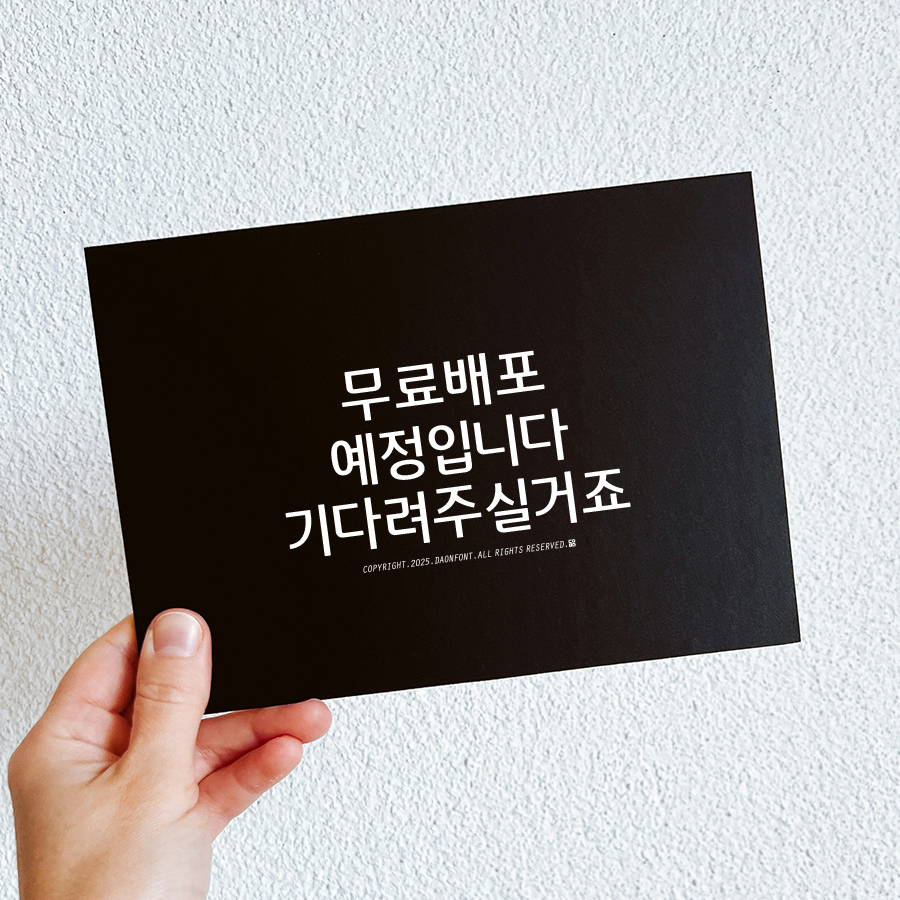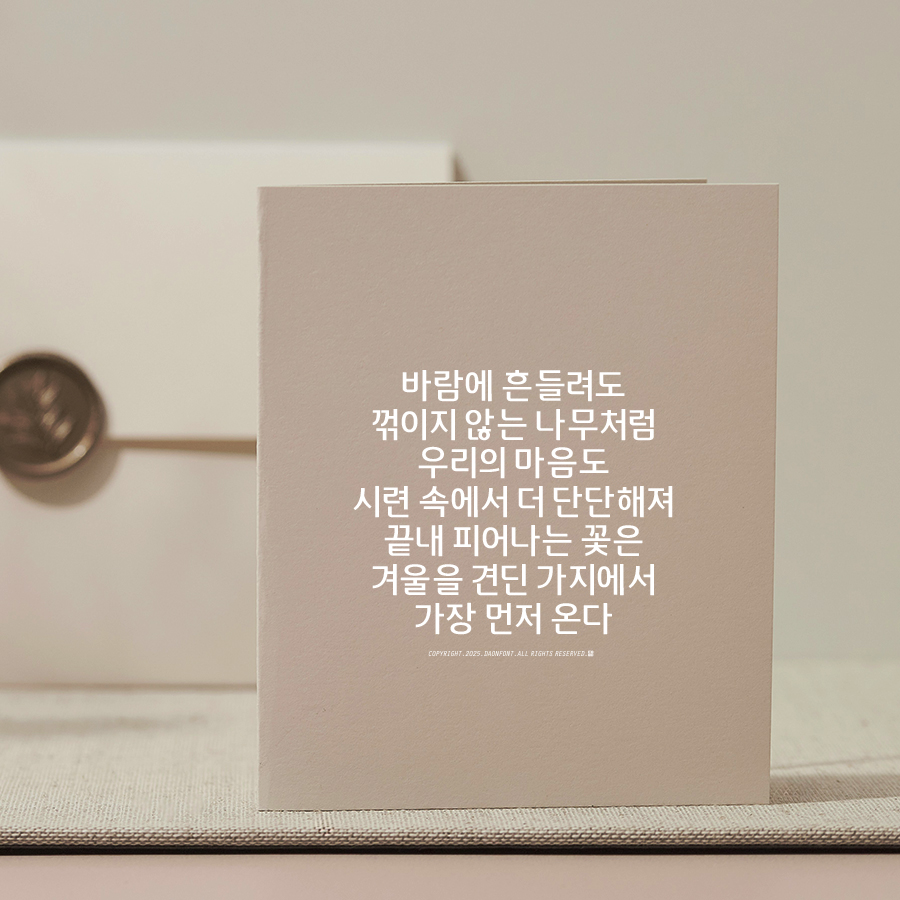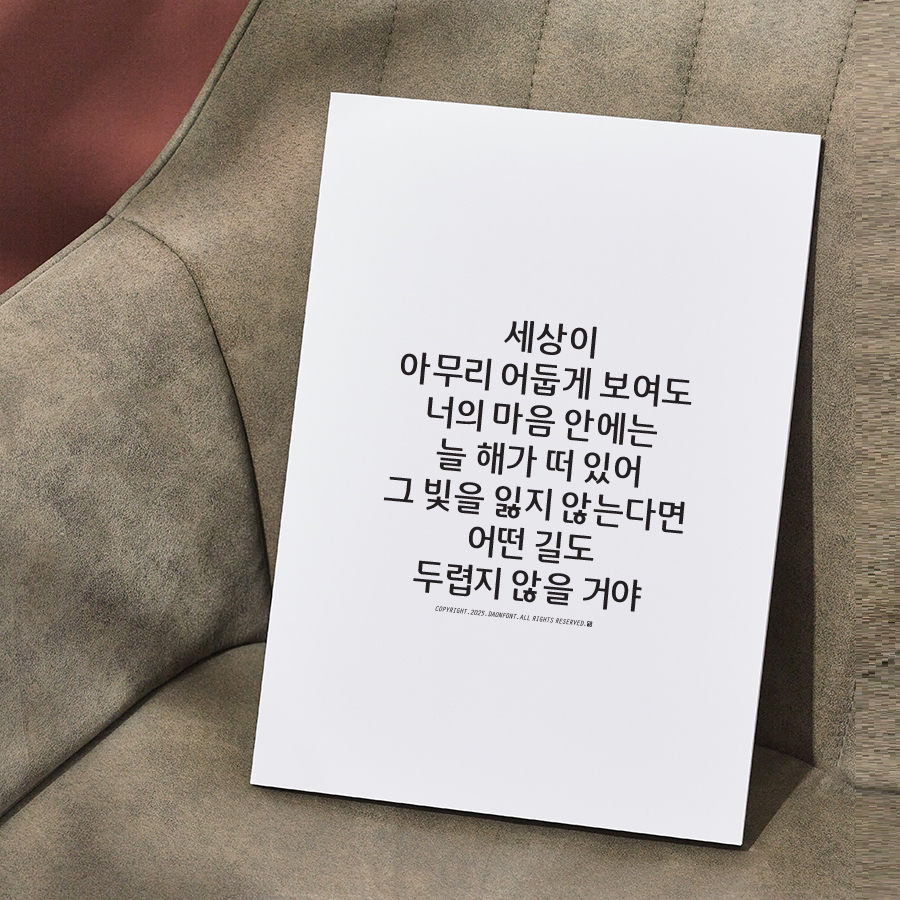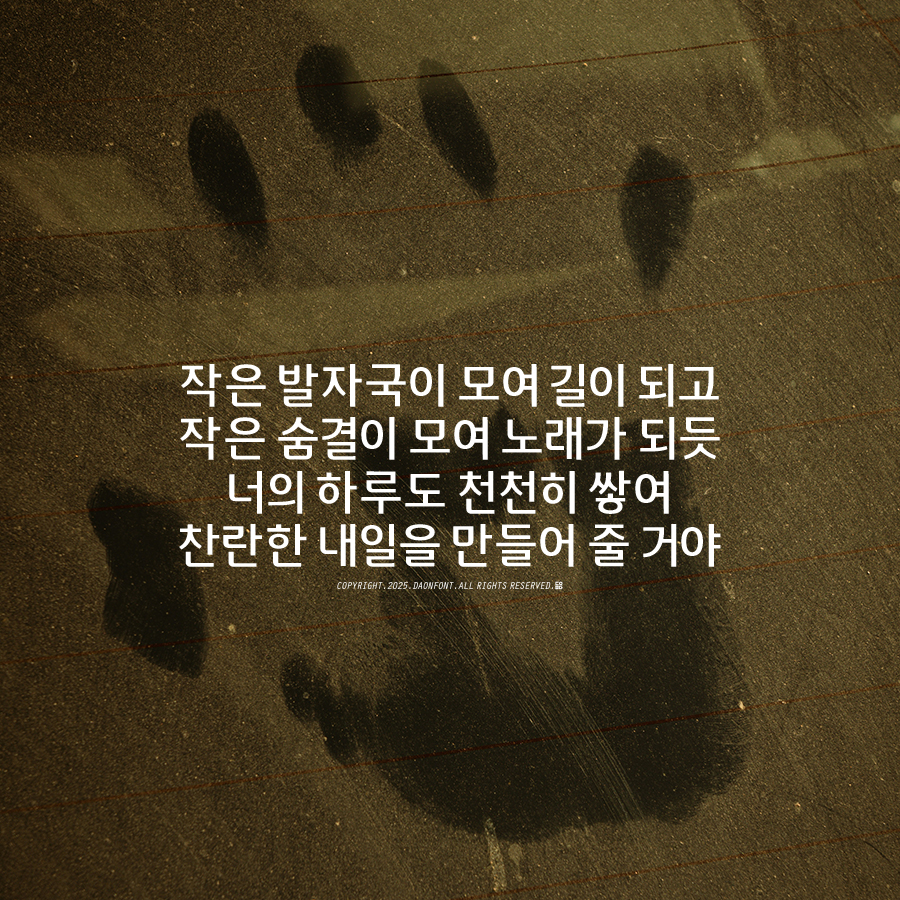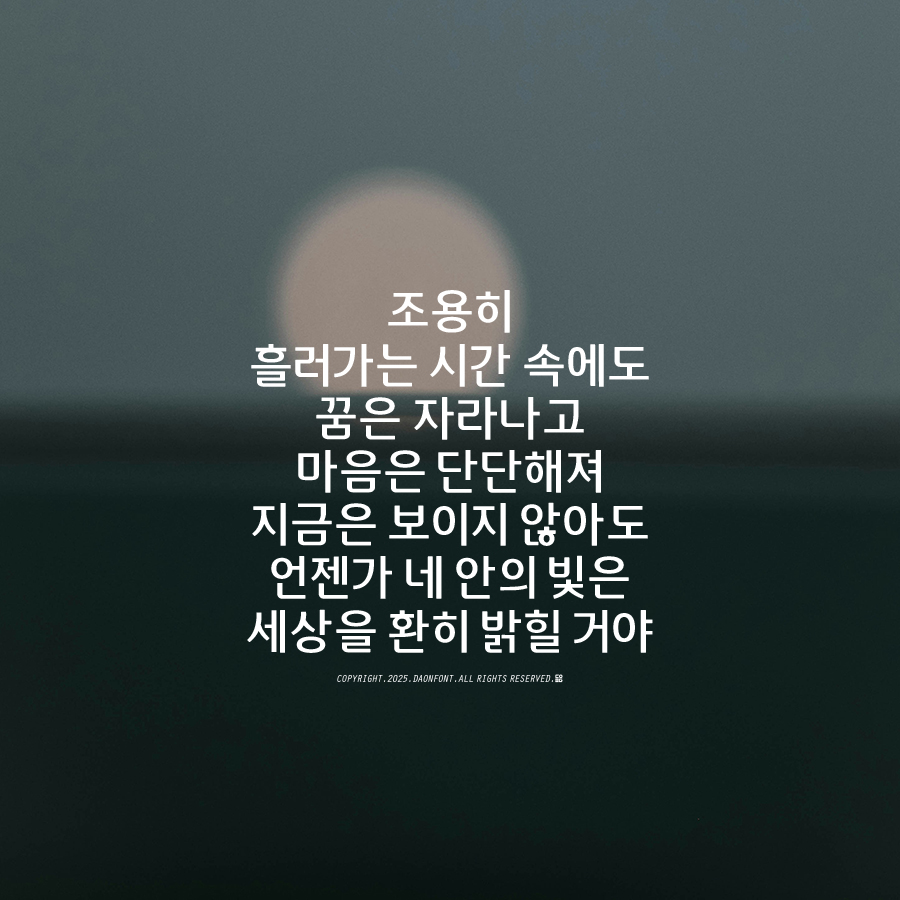
9월, 새로운 무료폰트가 공개됩니다.
이번 서체는 균형감 있는 구조와 뛰어난 가독성을 갖춘 고딕체로,
짧은 문구부터 긴 문장까지 안정적으로 담아낼 수 있도록 디자인되었습니다.
특히 담백하면서도 따뜻한 감성을 지니고 있어, 포스터, 카드뉴스, 캘리그라피 문구, 브랜드 메시지 등
다양한 디자인 작업에서 힘 있는 전달력을 보여줄 거예요.
마치 흔들림 없는 나무처럼, 당신의 메시지를 힘 있게 지켜줄 글자.